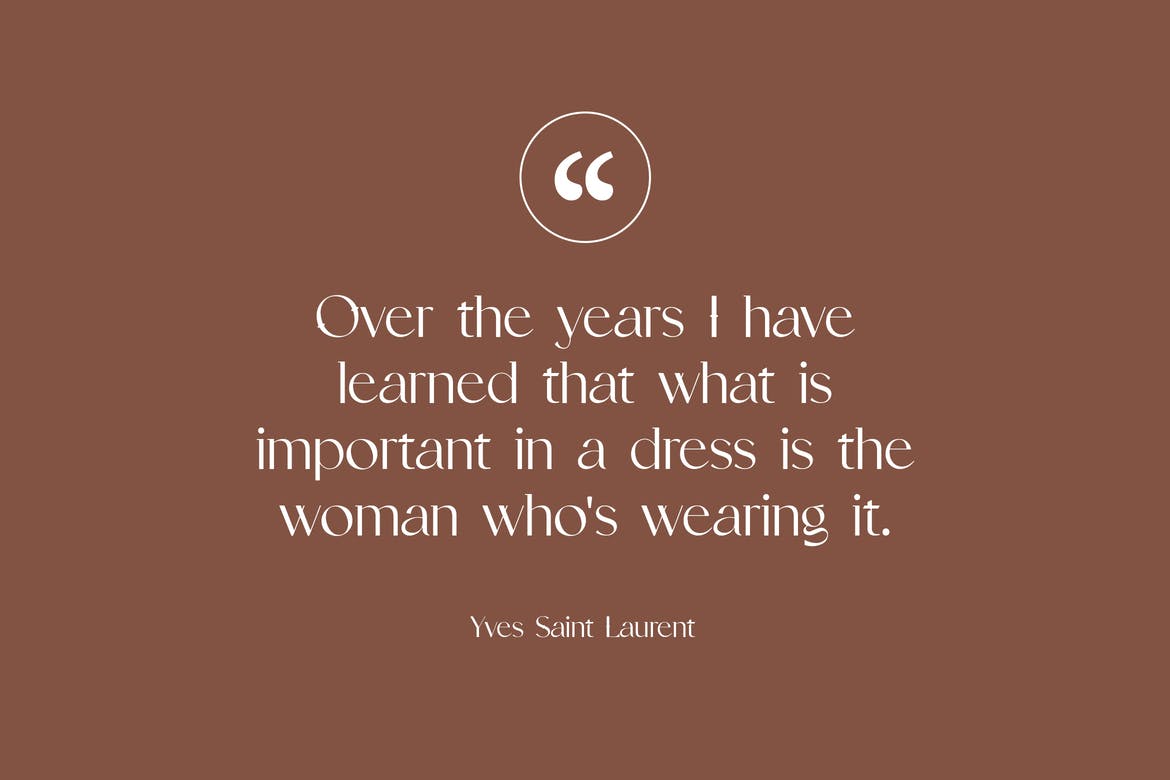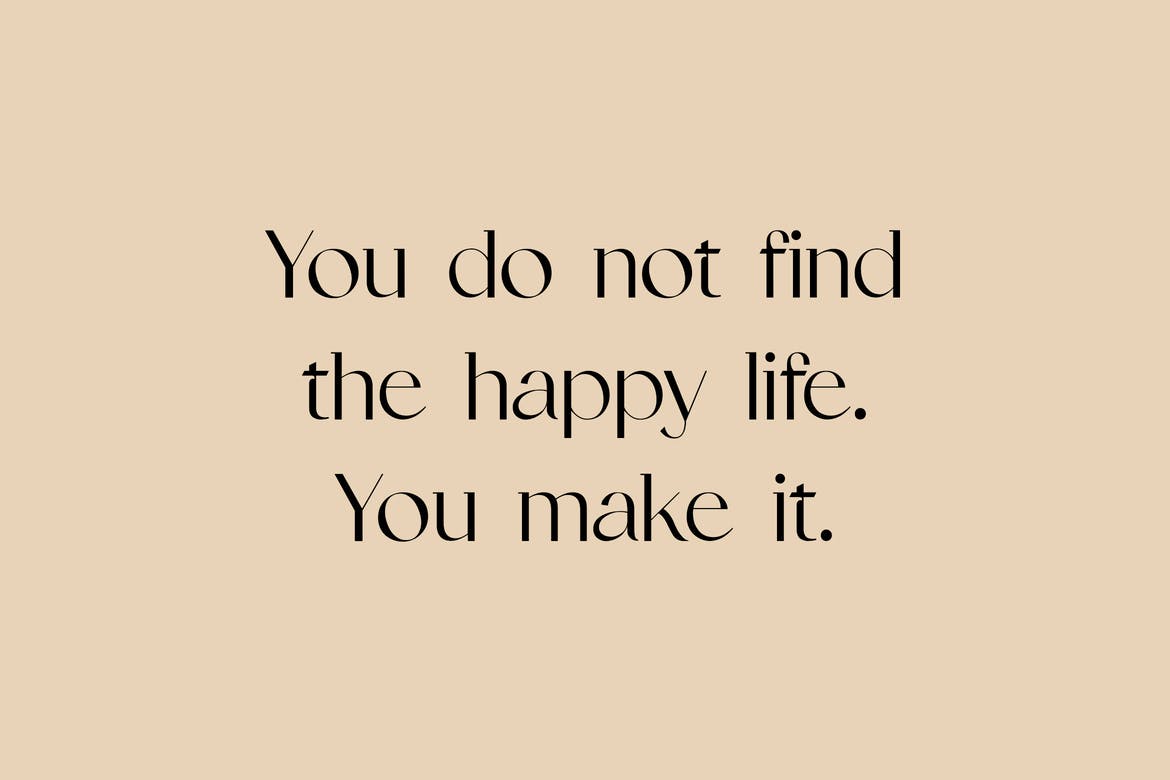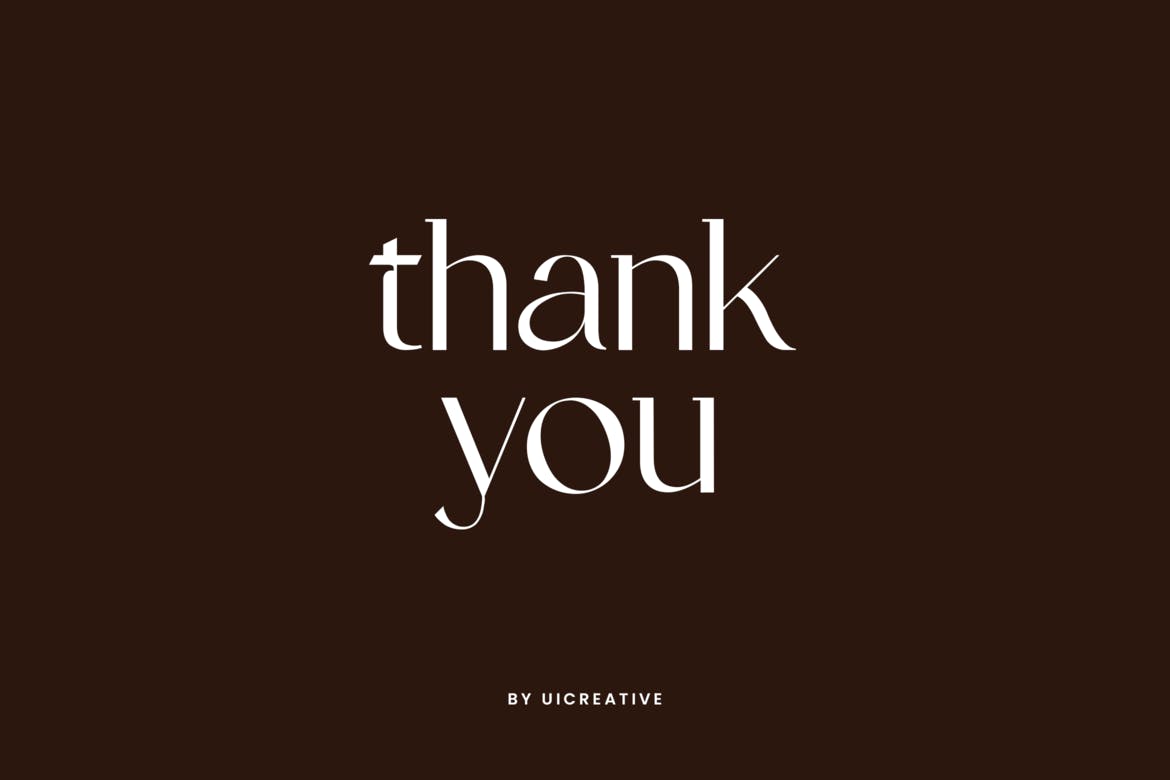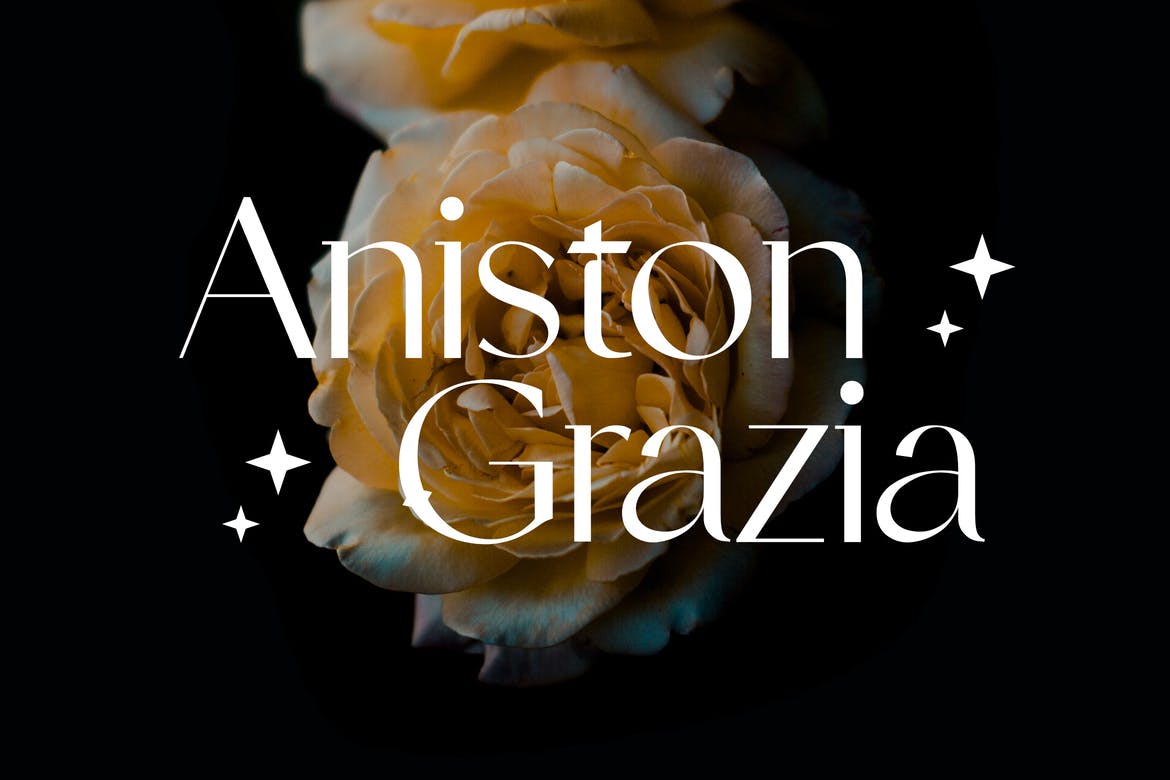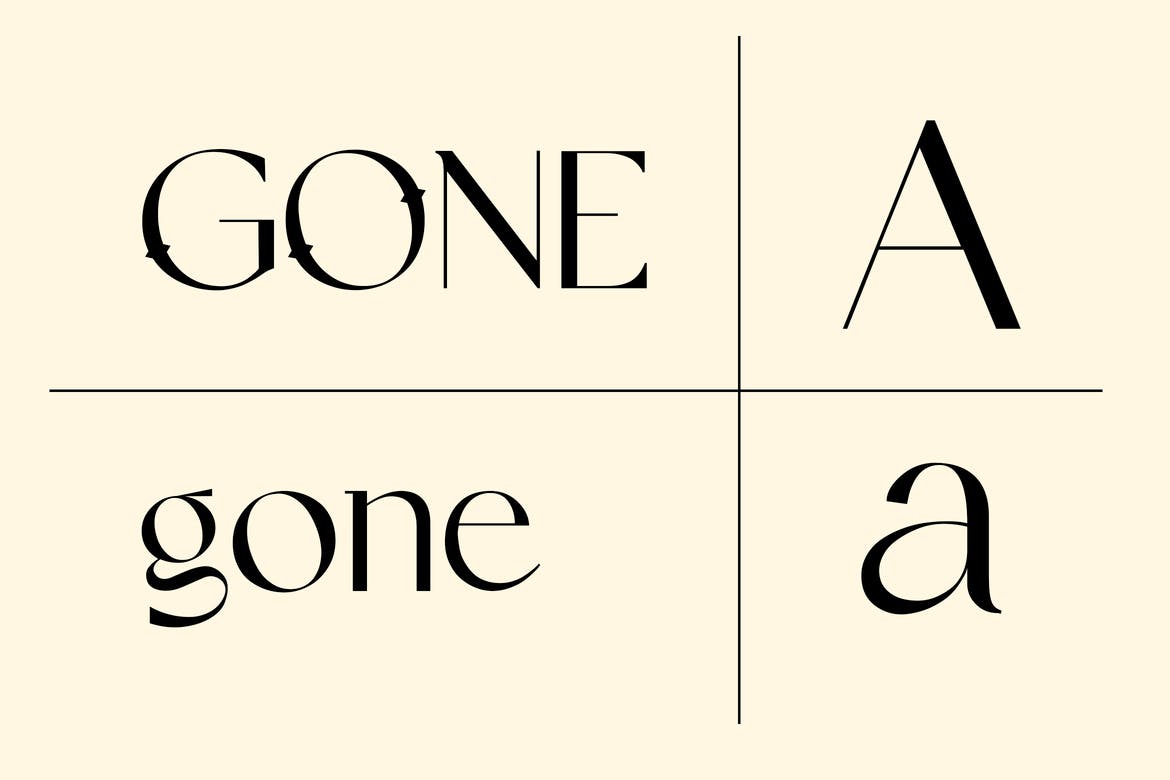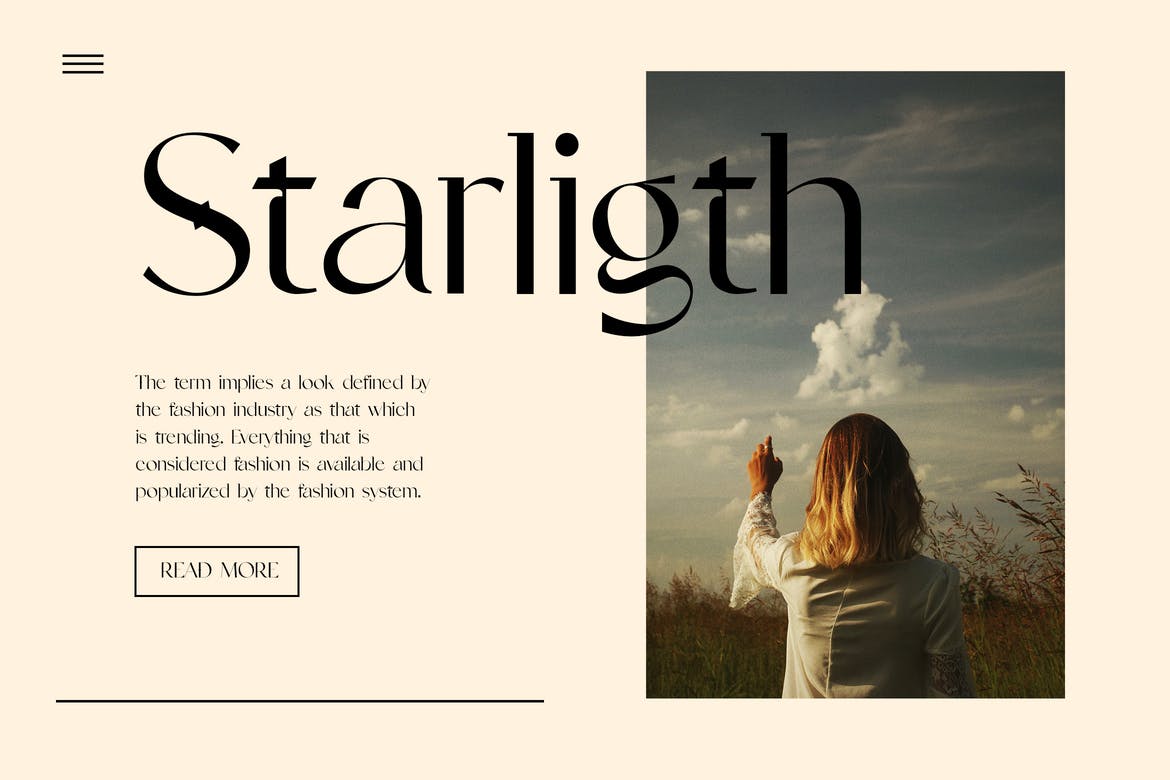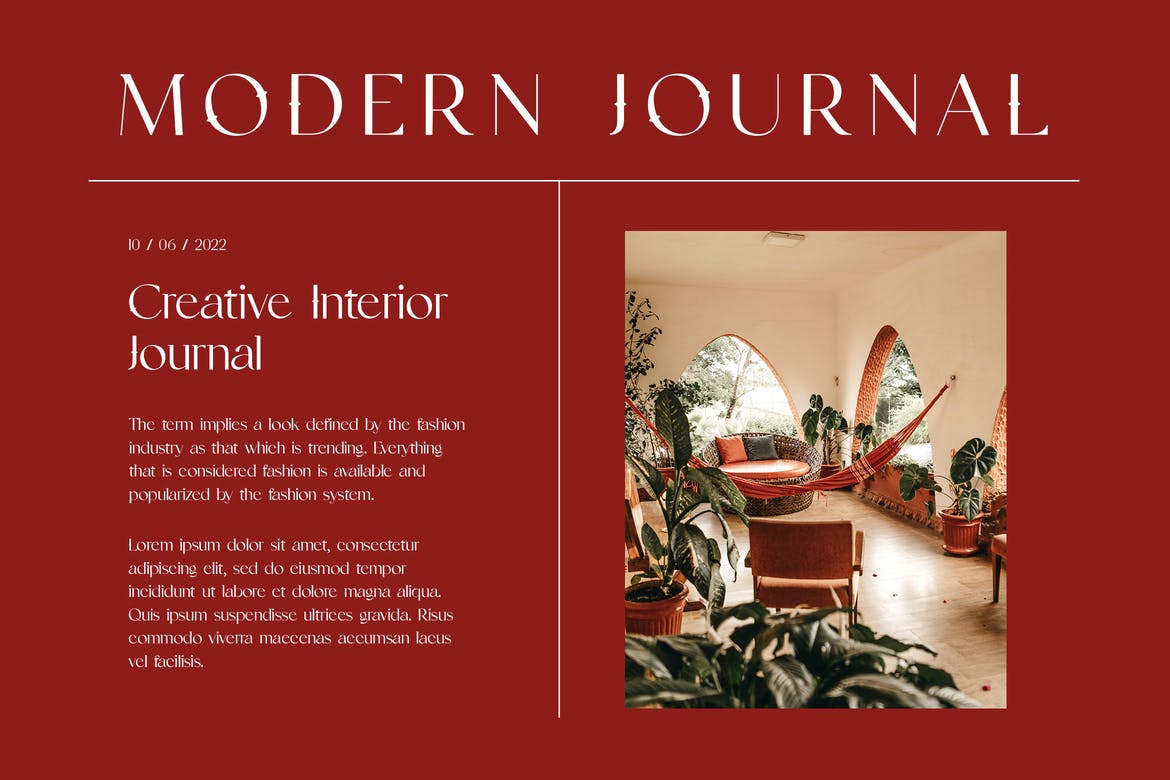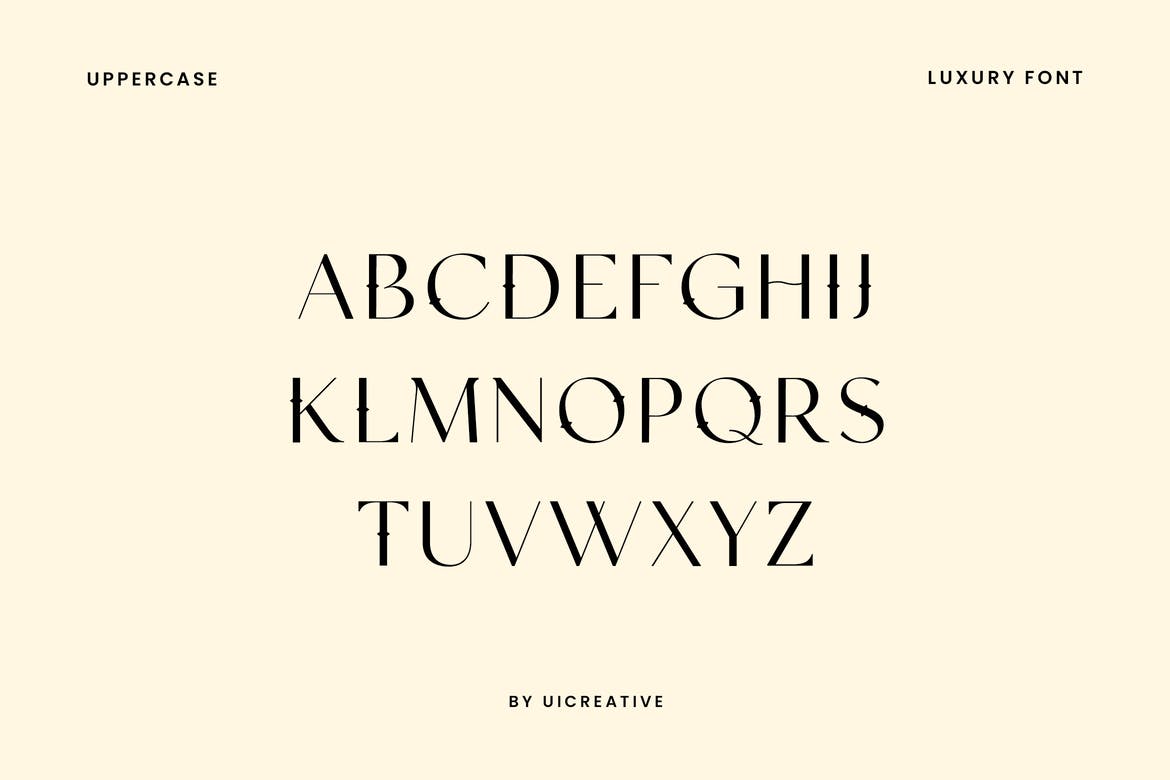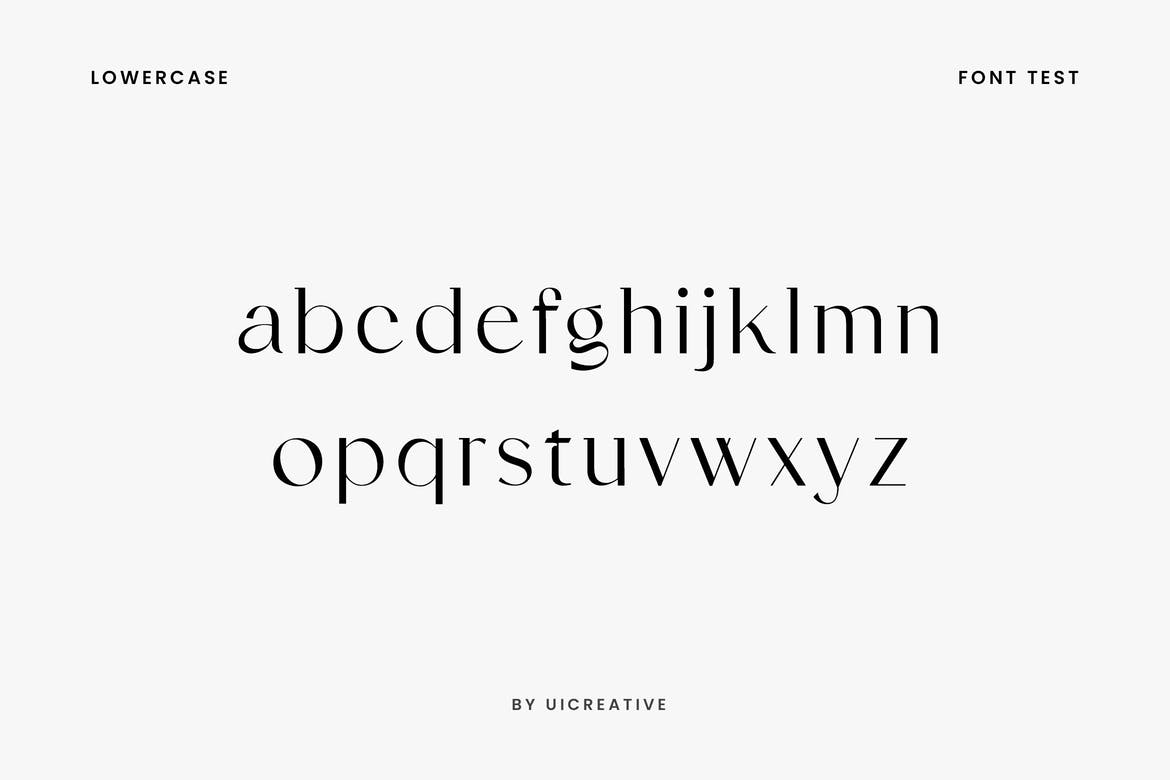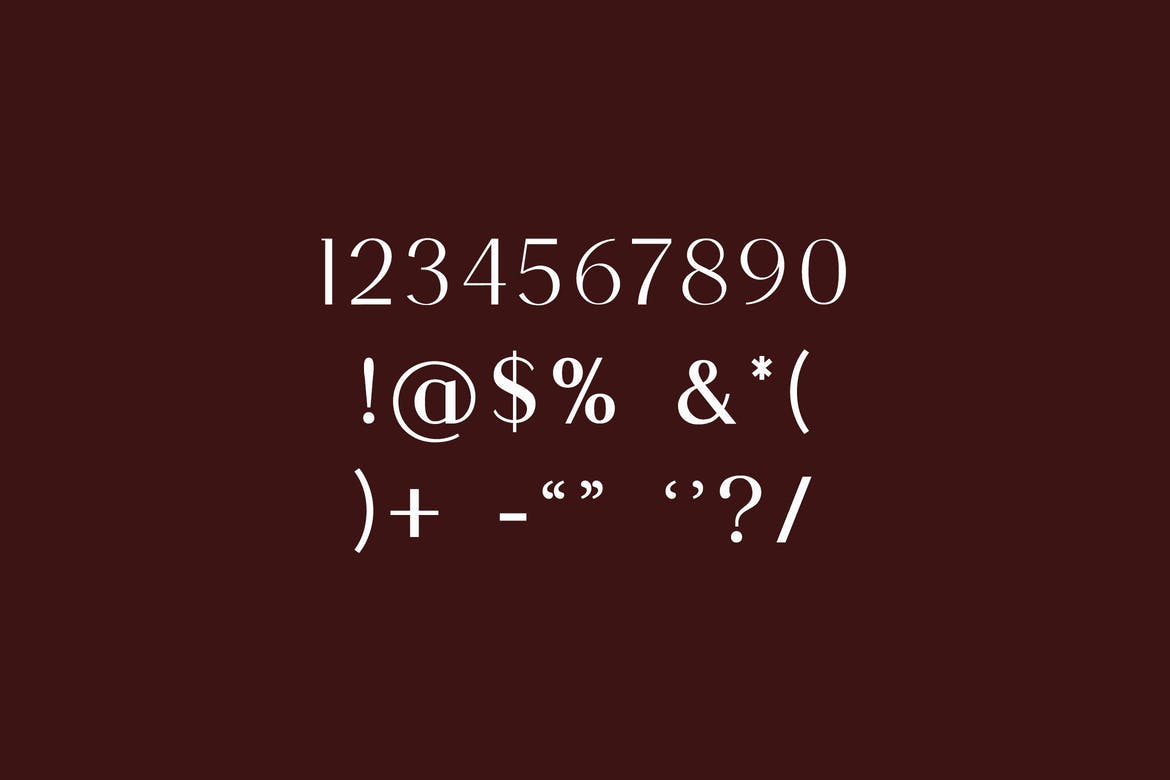
دانلود فونت پاراگون لاکچری سریف با کیفیت بالا
Paragone Luxury Serif Font
فونت پاراگون لاکچری سریف با طراحی مدرن و زیبا، مناسب برای پروژه‌های مختلف.
معرفی می‌کنیم محصول جدیدمان، نام آن فونت پاراگون لاکچری سریف است. این فونت سریف مدرن با طراحی زیبا و شیک، حس کلاسیک و معاصر را به ارمغان می‌آورد. این فونت به‌طور کامل برای انواع پروژه‌ها مناسب است، از جمله امضا، لوازم‌التحریر، لوگو، مراسم عروسی، نقل‌قول‌های تایپوگرافی، جلد مجله یا کتاب، هدر وب‌سایت، لباس، برندینگ، طراحی بسته‌بندی و بسیاری موارد دیگر. همچنین، برندینگ یا طراحی ویرایشی مرتبط با مد، هر دو ویژگی مردانه و زنانه را به نمایش می‌گذارد.